25 種 80 年代 Rad 字體,適用於完全正義的網站
已發表: 2018-10-2280 年代是一個有趣的設計時期。 它充滿了像素、霓虹燈、鍍鉻、銳邊、塊和完全管狀的樣式。 在本文中,我們將介紹 25 種字體,它們一定能幫助您捕捉 1980 年代的標誌性美學。
1. 貝肖爾
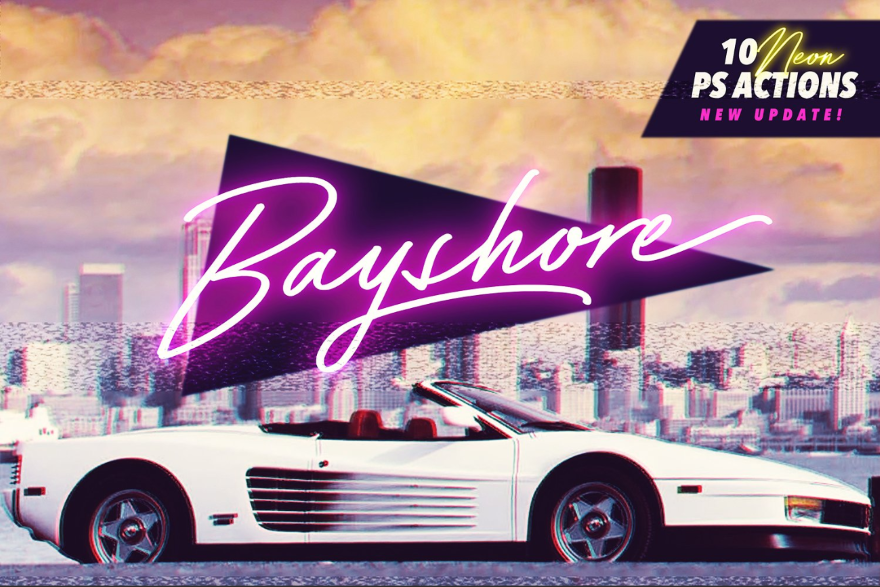
這種帶有霓虹色的字體讓我想在幾天不刮鬍子的情況下,穿著我的 rad 西裝外套在邁阿密的街道上開著我的法拉利,帶著涼爽的鼓聲。 這是一種手繪字體,非常適合徽標和產品。 它還包括一些 Photoshop 操作。
2. 跑者
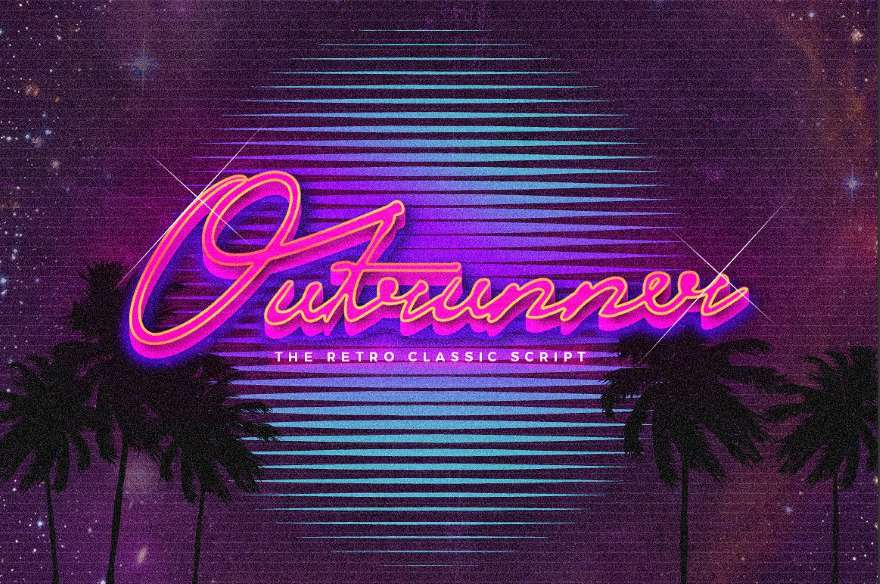
另一種“駕駛我的法拉利”字體讓我想用一些很棒的 80 年代音樂在全國范圍內比賽,這個字體使用鮮豔的顏色,非常適合徽標、標題、品牌等。
3. 激光84
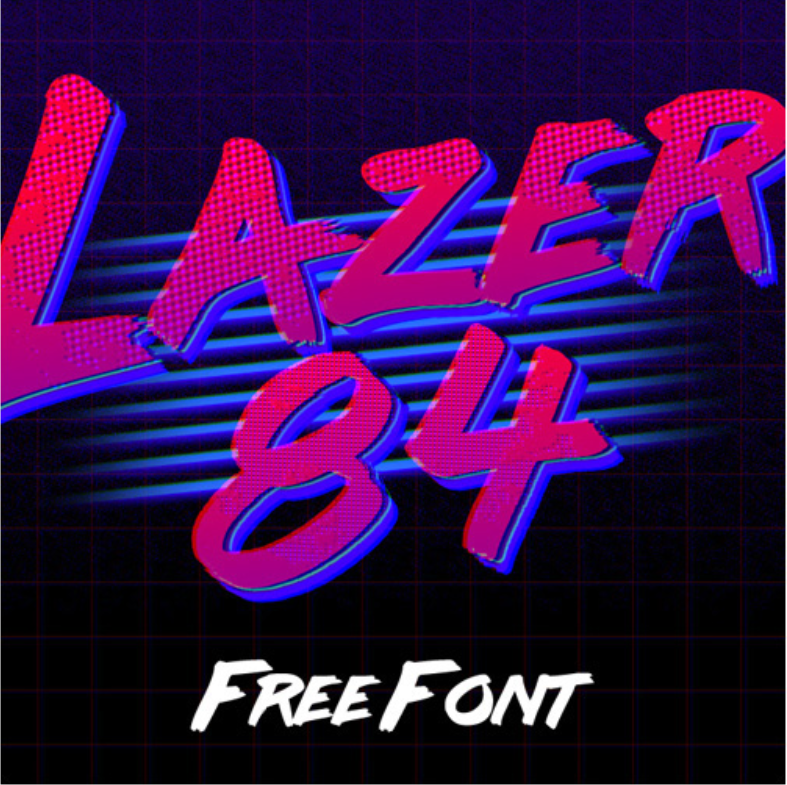
另一種讓我想起 80 年代遊戲、電影和音樂的字體,這個字體使用了一些激進的筆觸來提供一種帶有和不帶有顏色陰影和陰影的字體。 它非常適合標題、標題、海報、傳單、徽標等。
4. 雷暴
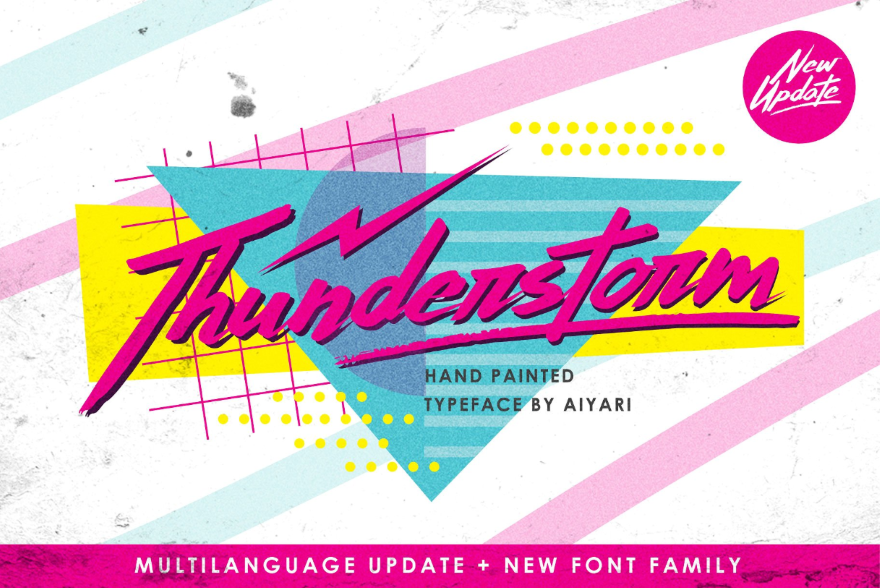
這種字體是手繪的,帶有粉紅色和淺綠色,非常適合任何復古、迪斯科甚至是 90 年代的垃圾網站。 它非常適合徽標、書籍、服裝、標題等。 它包括字形。
5. 渥太華
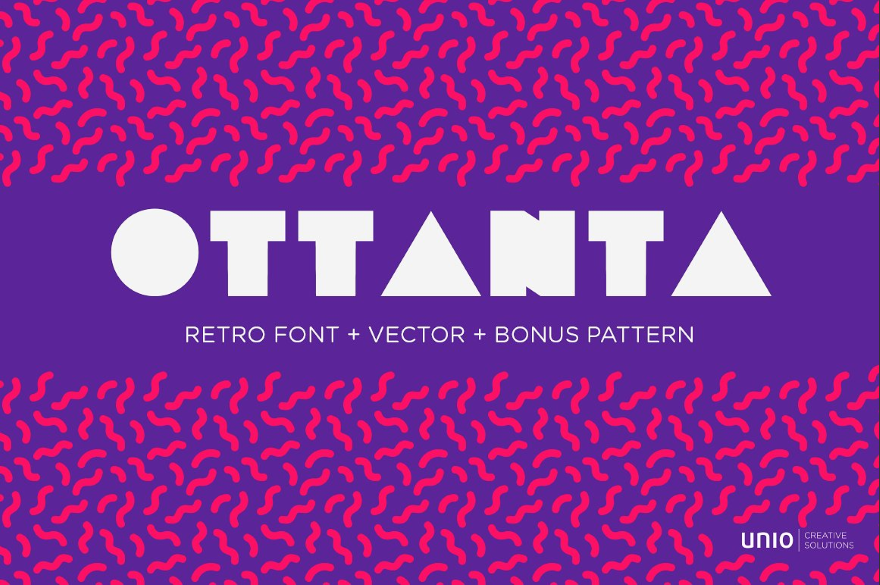
這種字體喚起了人們對電影、雜誌和故障廣告的回憶。 其厚實而四四方方的外觀非常適合用於徽標、標題、橫幅、海報等。
6. 奧蘭多
這種複古字體展示了 80 年代在廣告、海報和音樂行業中非常流行的一些分層。 它還包括一組填充字體,使這組字體非常適合任何需要 rad 字體的東西。
7. 墓地之刃
用這種字體重溫 80 年代的重金屬時代。 尖銳的點和角度以及不會出錯的風格,這是任何重金屬網站的絕佳字體。 現在我必須加大失真度。
8. 銅
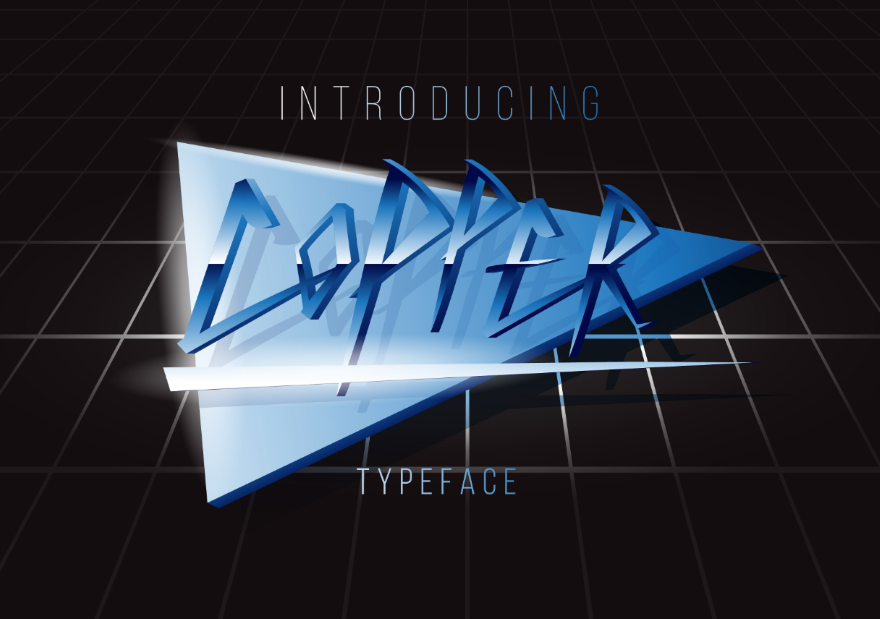
這種字體帶你去看電影。 它具有簡單的設計,只需幾筆筆觸即可保持線條筆直,非常適合用於徽標、雜誌、標題、海報、樂隊等。
9. 黑客
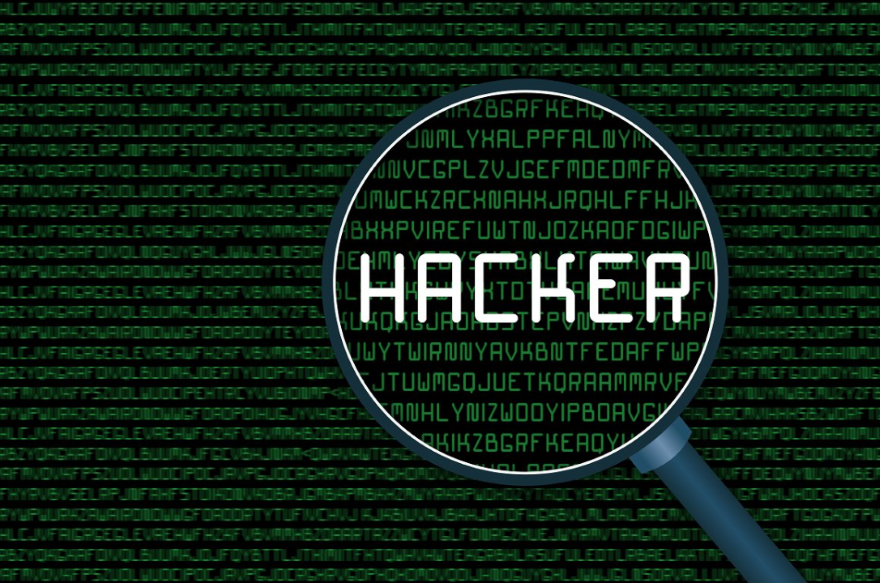
這是另一種將您帶回電影的字體——這次是運行 UNIX 的精美公司計算機,它隱藏了所有公司機密。 這種字體非常適合任何 IT/IS 需求,包括在線商店、安全性、網絡或任何包含較舊計算機技術的東西。
10. 吃了一點
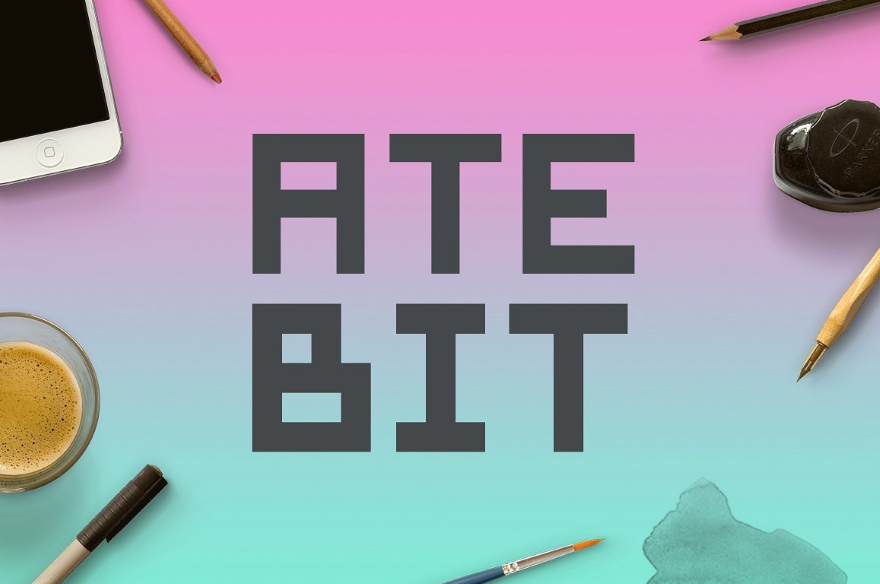
這種字體帶回了過去 8 位遊戲的美好時光,當時遊戲機佔用了四分之一,您必須在下一波外星人襲擊之前學習這種模式。 當您想以 80 年代的感覺脫穎而出時,這種字體非常適合與遊戲有關的任何事情。
11.Bitcraft
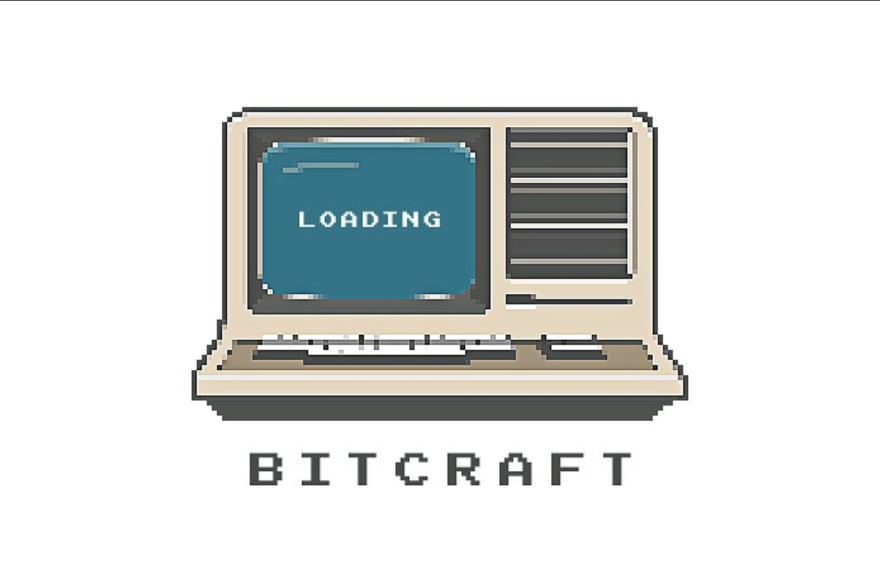
這個讓我想拿起我的 C64 玩一輪 Zork(品嚐字母。輸入。“它嘗起來像一封信”)。 這是適用於任何類型的 8 位插圖(包括圖標、海報等)的絕佳字體。
12. 剃刀
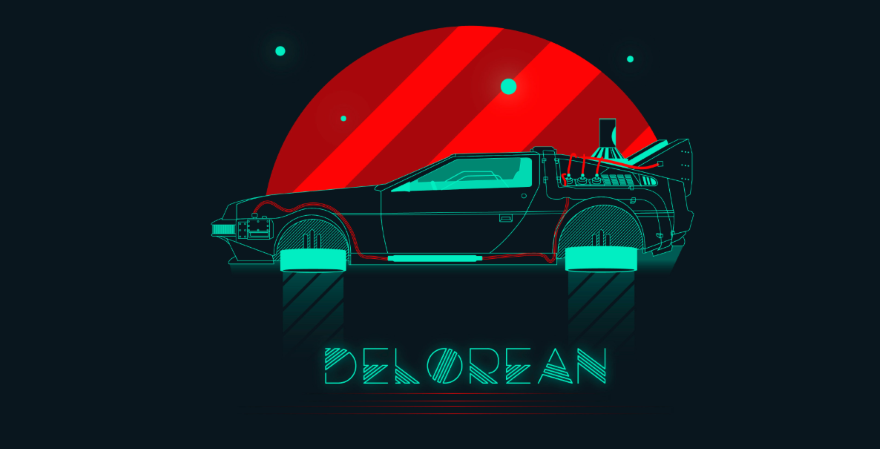
使用這種激光蝕刻的多行字體,再乘車前往邁阿密的海灘。 它是海報、徽標等的絕佳選擇。 它包含 CSS 以使您的網站閃耀。
13. 約翰尼發燒
帶回辛辛那提 80 年代收音機的美好回憶,Johnny Fever 是一種獨特的塊狀字體,非常適合標題、標題、徽標、產品等。
14. Uniwars
這一款具有流暢的 80 年代科幻外觀,有 16 種不同的風格。 這是一種外展字體,其靈感來自日本的標識,非常適合標題、標題、徽標、海報或任何需要非典型風格的東西。
15. Cyberglass JNL
這種字體旨在幫助您贏得機器人啟示錄,這在機器人從未來回來終結您的時候總是很方便。 當這種情況發生時,我個人討厭它。 它包括兩種風格,非常適合與科幻或計算機相關的任何內容。
16. 斯科特
這是另一種科幻字體,具有許多棱角分明的樣式,肯定會讓您的科幻網站與眾不同。 這是下一代,下一代。 這是標題、徽標、傳單等的絕佳選擇。
17.伊沃克
這種字體讓我想起了可以摧毀任何帝國的可愛的小抱熊戰士。 他們肯定有自己的風格,會為孩子的網站、書籍或產品製作一些有趣的標誌或標題。
18. 火箭騎士
超過 80 年代的電影、遊戲、書籍和電視節目都使用了這種科幻字體。 憑藉其銳利的角度和霓虹色,除了 80 年代科幻之外,這種字體不會被誤認為是其他任何東西。
19. 狮心
任何看過 80 年代哥特式電影和書籍的人都會覺得這種字體很熟悉。 這種字體非常適合關注中世紀和哥特歷史的網站和書籍。
20. 尖叫聲
如果你喜歡整夜搖滾,你可能已經看過一兩張字體與這張專輯相似的專輯。 它包括兩種風格,是任何專注於硬搖滾的網站或傳單的絕佳選擇。 它特別適合標題和徽標。